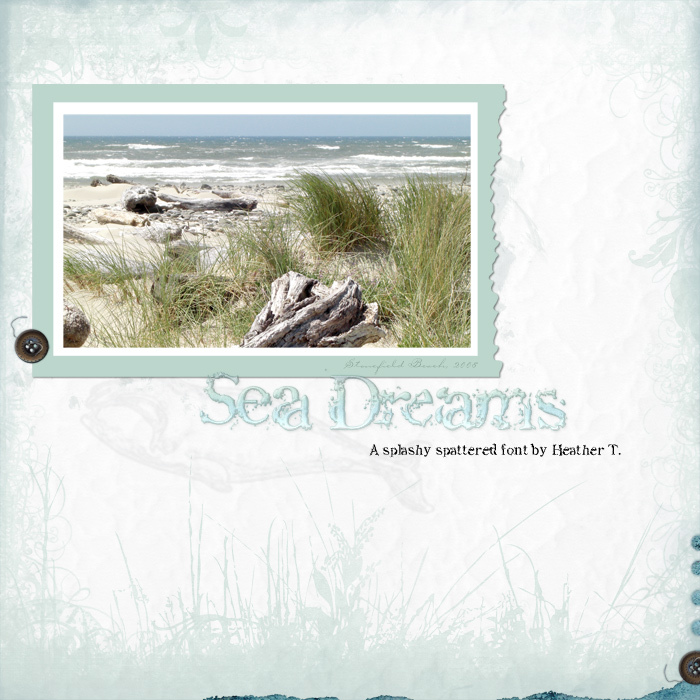
Sea Dreams ist eine kostenlose, erodierte Display-Schrift von Heather Taylor, die 2008 mit einem rauen, wettergegerbten Charakter entworfen wurde. Zerfetzte Kanten, verstreute Lücken und ungleichmäßige, tintenartige Flecken verleihen den Buchstaben die Anmutung eines alten Drucks, der durch Salz, Sand oder jahrelange Beanspruchung beschädigt wurde.
Die brüchige Textur sorgt für ein unmittelbares Gefühl von Verfall bei Albumcovern und Veranstaltungsplakaten und verleiht Horrortiteln eine beunruhigende Note. Verwenden Sie diese kostenlose Schriftart für Verpackungen von Craft-Getränken, redaktionelle Cover oder wettergegerbte Markenidentitäten, bei denen die abgenutzte Typografie mit Fotos und haptischen Materialien interagieren kann, anstatt wie eine reine digitale Ebene zu wirken.